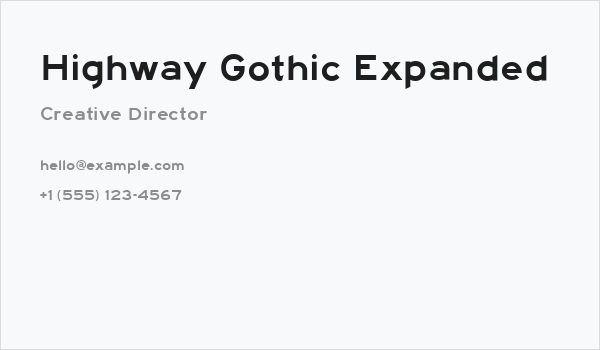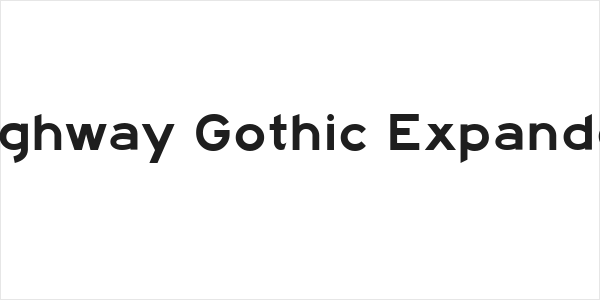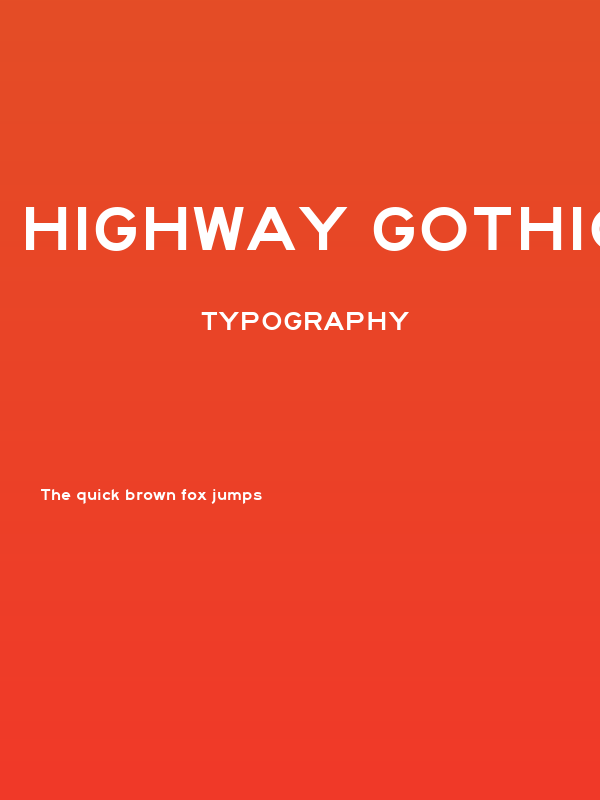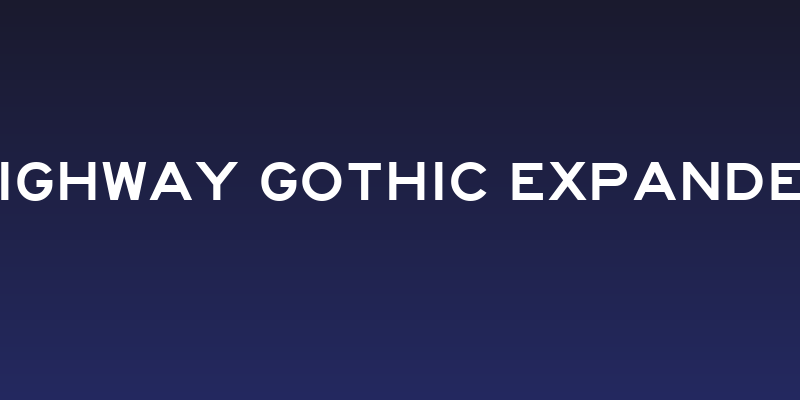
Highway Gothic Expanded Font
| Kategorien | Gothic |
| Breite | Expanded |
| Anwendungsfall | Headlines, Signage, Logos |
| Vorgeschlagene Projekte | Ideal for highway signage, advertising billboards, corporate branding, and any project requiring clear and impactful text. |